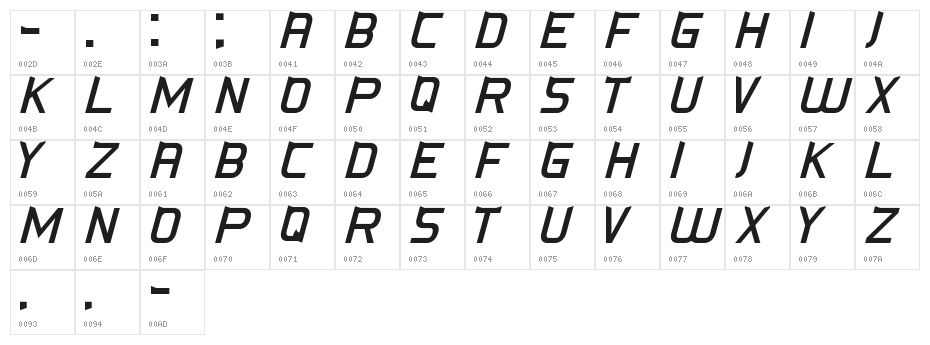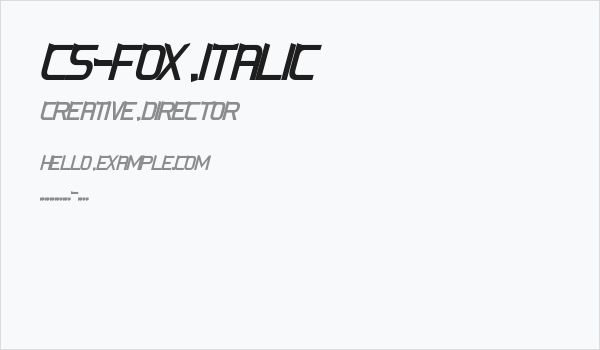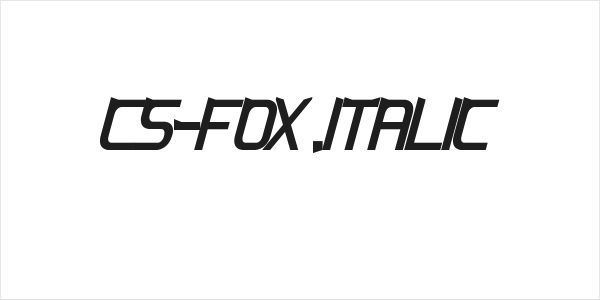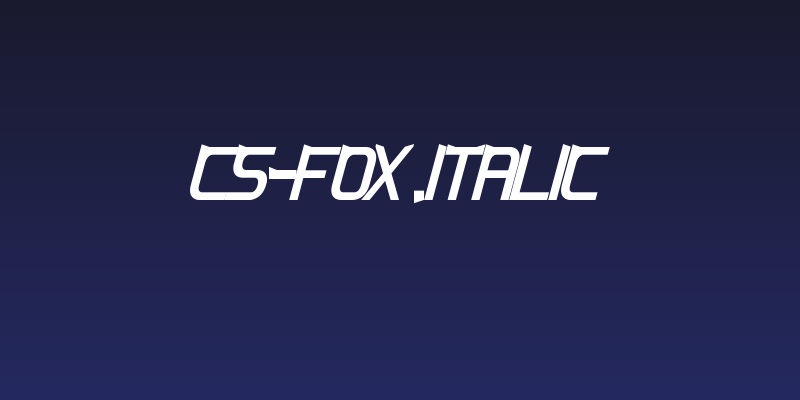
CS-Fox Italic Font
| Gewicht | Italic |
| Kategorien | Thick |
| Anwendungsfall | Logos, Headlines, Branding |
| Vorgeschlagene Projekte | Ideal for branding, sports team logos, automotive designs, and dynamic advertising. |
CS-Fox Italic